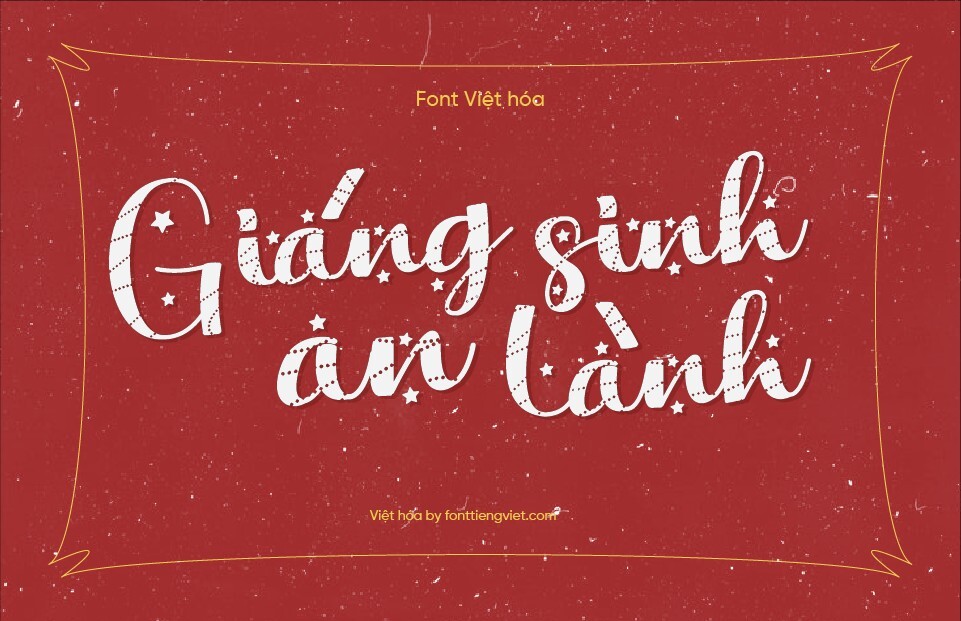
Giới thiệu về Font Việt hóa 1FTV VIP For Christmas – Giáng sinh
Mùa lễ hội cuối năm đang đến gần, nhu cầu tìm kiếm các mẫu Font Chữ mang đậm phong cách lễ hội ngày càng tăng cao. Trong đó, Font Việt hóa 1FTV VIP For Christmas – Giáng sinh nổi lên như một lựa chọn hàng đầu cho các nhà thiết kế tại Việt Nam. Đây là bộ phông chữ được tinh chỉnh kỹ lưỡng, hỗ trợ đầy đủ tiếng Việt giúp bạn truyền tải thông điệp ấm áp của mùa Noel một cách trọn vẹn nhất. Với đường nét mềm mại và tinh tế, bộ font này không chỉ mang lại vẻ đẹp thẩm mỹ mà còn tạo nên sự chuyên nghiệp cho mọi tác phẩm đồ họa từ thiệp mời đến biểu ngữ quảng cáo.
Đặc điểm nổi bật của bộ font lễ hội này
Bộ Font Việt hóa 1FTV VIP For Christmas – Giáng sinh sở hữu những nét vẽ uyển chuyển, gợi liên tưởng đến những dải ruy băng và không khí rộn ràng của đêm đông. Điểm đặc biệt của phiên bản VIP này chính là khả năng hiển thị mượt mà trên nhiều nền tảng khác nhau, từ in ấn đến hiển thị kỹ thuật số. Bạn có thể dễ dàng ứng dụng để thiết kế thiệp chúc mừng, bìa sách hoặc các ấn phẩm truyền thông cho nhà trường và doanh nghiệp.
Cách ứng dụng Font Việt hóa 1FTV VIP For Christmas – Giáng sinh hiệu quả
Để tận dụng tối đa vẻ đẹp của font chữ này, người dùng nên kết hợp với các tông màu chủ đạo của Giáng sinh như đỏ, xanh lá cây và vàng kim. Việc sử dụng font chữ trong các tiêu đề lớn sẽ giúp thu hút sự chú ý ngay lập tức. Ngoài ra, tính năng Việt hóa giúp loại bỏ hoàn toàn lỗi gõ dấu, đảm bảo tính thẩm mỹ cao nhất cho văn bản. Hãy thử áp dụng vào các dự án giáo dục hoặc trang trí lớp học để tạo không khí lễ hội vui tươi cho các em học sinh.